외출한 지 얼마 안된 것 같은데 땀이 주르륵 흐르고, 숨이 턱턱 막히는 요즘입니다. 더위를 이기는 방법으로 서늘한 호러물을 찾는 분들이 많으실 텐데요. 산돌구름이 타는 듯한 여름을 시원하게 식혀줄 공포 폰트를 모았습니다.
1. 산돌 / Sandoll 으스스
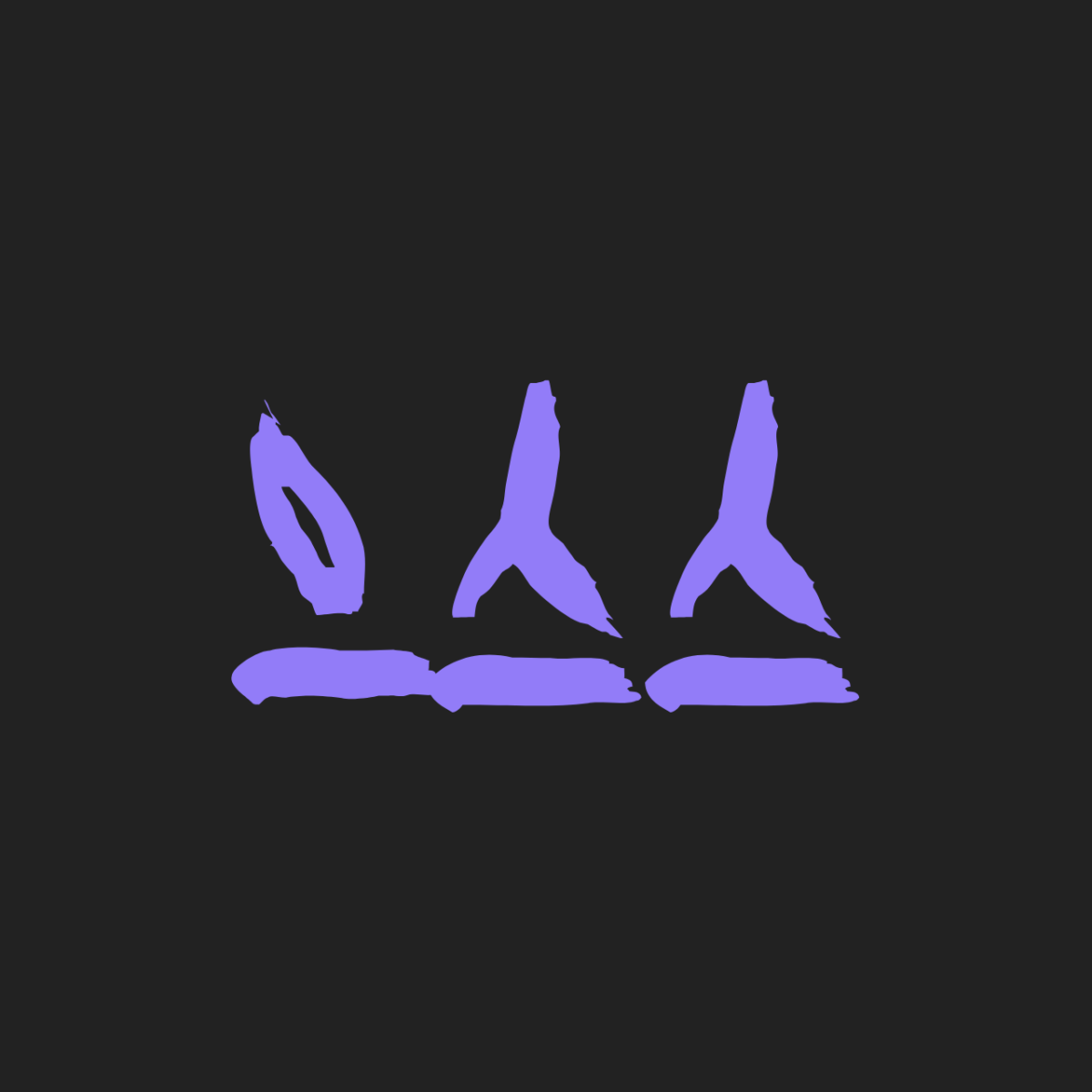
‘Sandoll 으스스’는 ‘Sandoll 끼기긱’과 함께 산돌 호러 프로젝트로 제작된 폰트입니다. ‘Sandoll 으스스’는 도깨비불이나 호롱불, <부산행>이나 <킹덤>에 나오는 한국 좀비 등 동양의 주술적인 요소에서 영감을 받은 폰트예요. 마치 도깨비불이 아른거리는 것 같기도 하고, 좀비떼가 몰려오는 듯한 모습이 그려지기도 해요. 이름만 봐도 서늘해지는 ‘Sandoll 으스스’로 한여름 밤 공포체험과 어울리는 제작물을 만들어보세요!
2. 디자인210 / 210 스위트홈
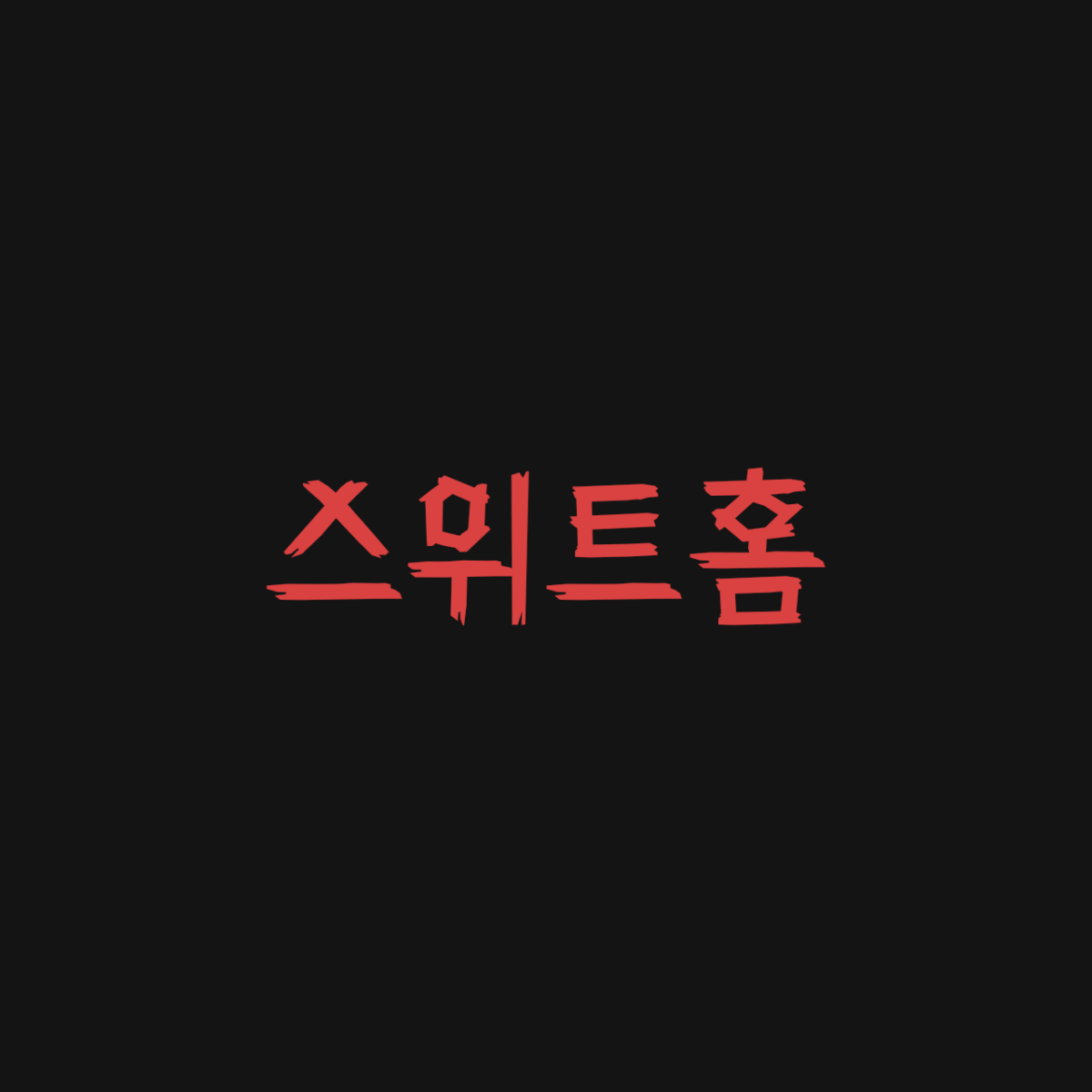
‘210 스위트홈’은 스산하고 거친 느낌을 콘셉트로 제작된 폰트입니다. 거칠게 표현된 크랙들이 마치 귀신의 집을 연상시키며 음산한 이미지를 강조하고 있어요. 긴장감 속 빠르게 쓴 느낌으로 디자인된 ‘ㅅ’과 같은 형태들에서 개성이 돋보이는 폰트입니다. 강렬하고 스산한 느낌의 타이틀이나 영상 자막에 활용하시는 것을 추천드려요!
3. 디엑스코리아 / DX납량특집
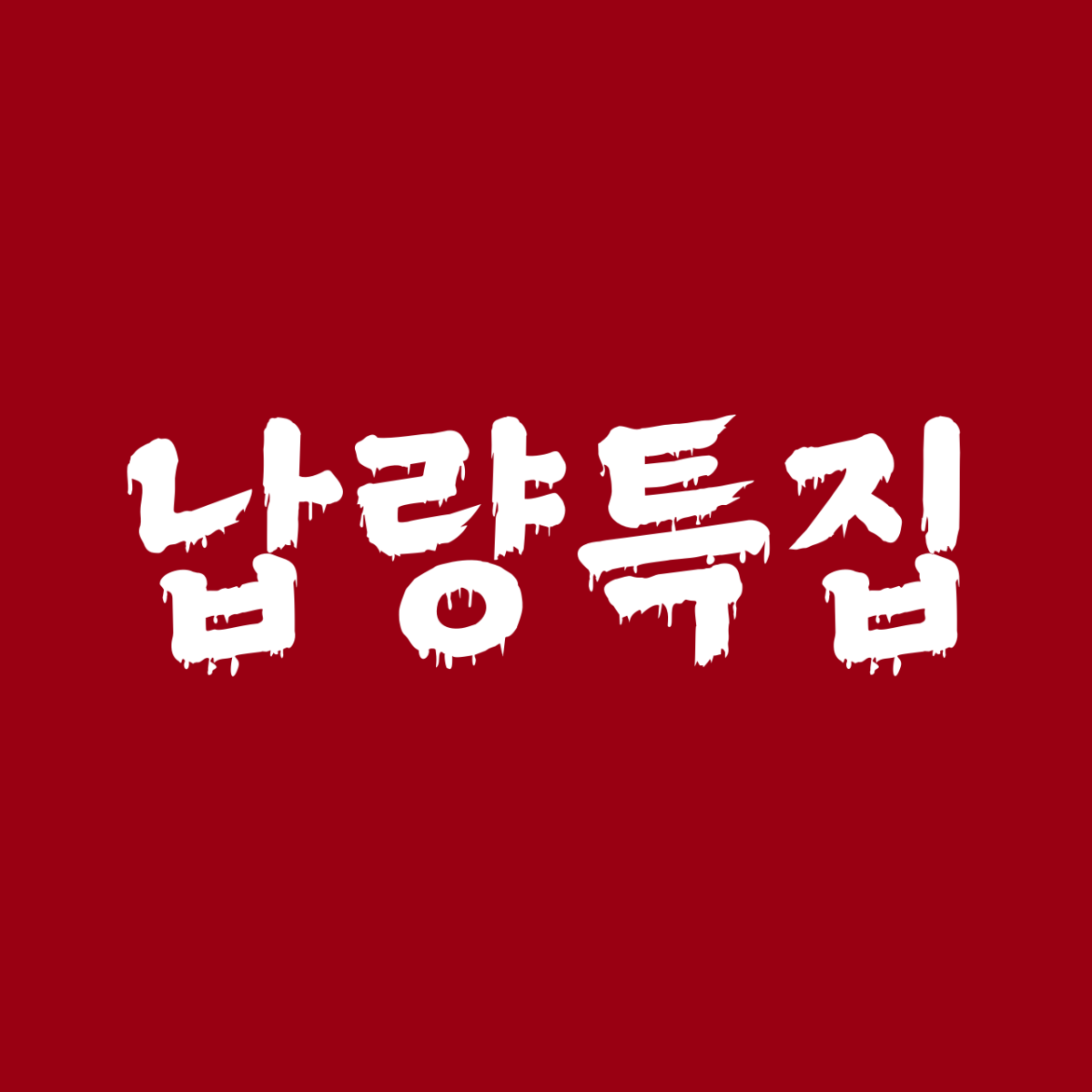
이름 그대로 ‘납량특집’에 나올 것 같은 콘셉트로 디자인된 ‘DX납량특집’입니다. 붓으로 쓴 듯한 손글씨 형태에 피가 흘러내리는 듯한 디테일이 인상적인 폰트예요. 그라데이션이나 글자에 효과를 입혀 사용하면 무서운 분위기를 한껏 강조할 수 있어, 공포 테마에 찰떡인 폰트로 추천합니다.
4. 닥터폰트/ DR좀비
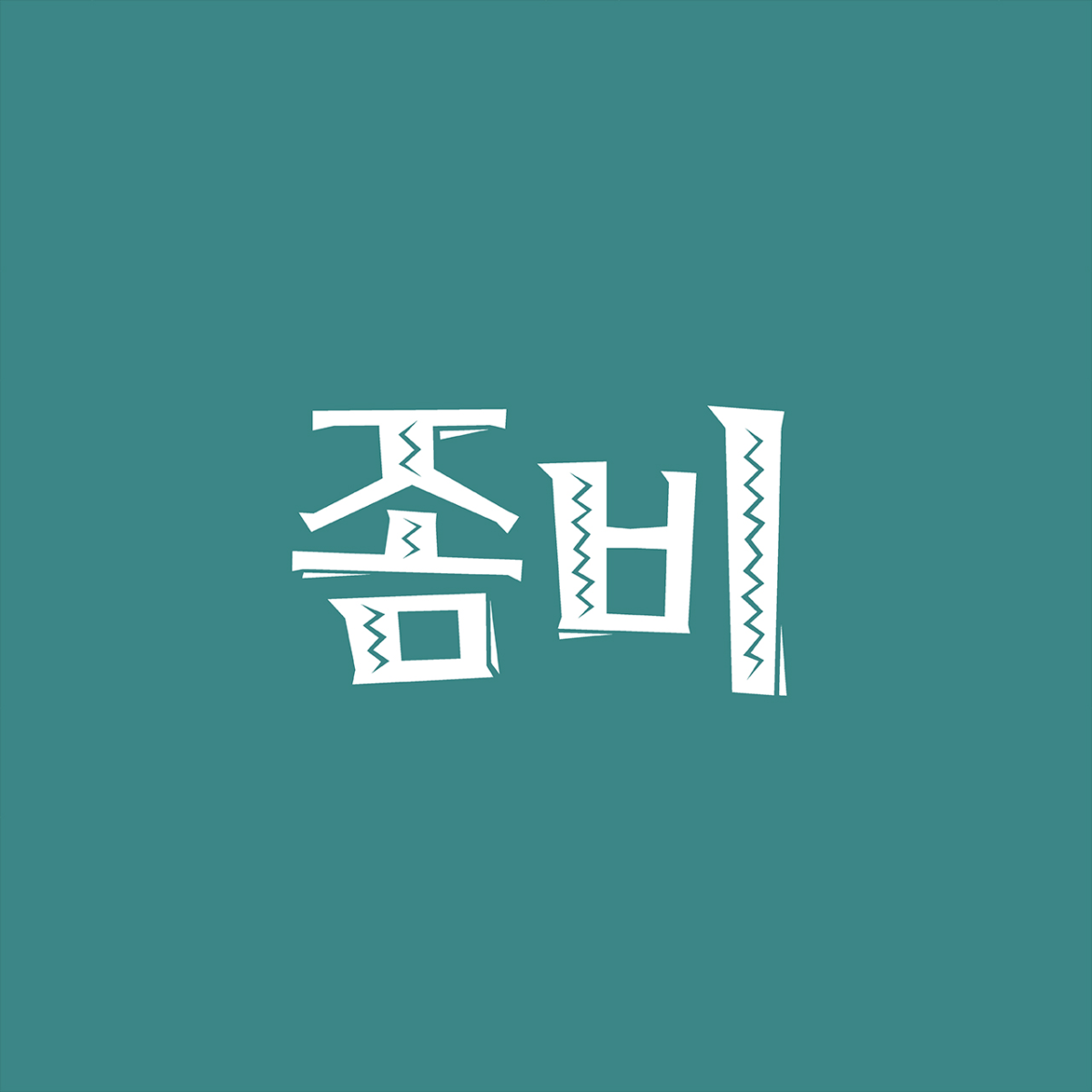
‘DR좀비’는 자소를 조금씩 기울이고 비틀어 날카롭게 깎은 형태가 특징인 폰트입니다. 갈라진 틈새를 표현한 것을 기본으로 외곽선, 그림자를 표현한 총 6가지 스타일을 가지고 있어 폰트만으로 디자인을 완성할 수 있다는 장점이 있어요. 좀비가 나올 것만 같은 으스스한 분위기의 도서, 포스터, 영상에 사용하시는 것을 추천드려요!